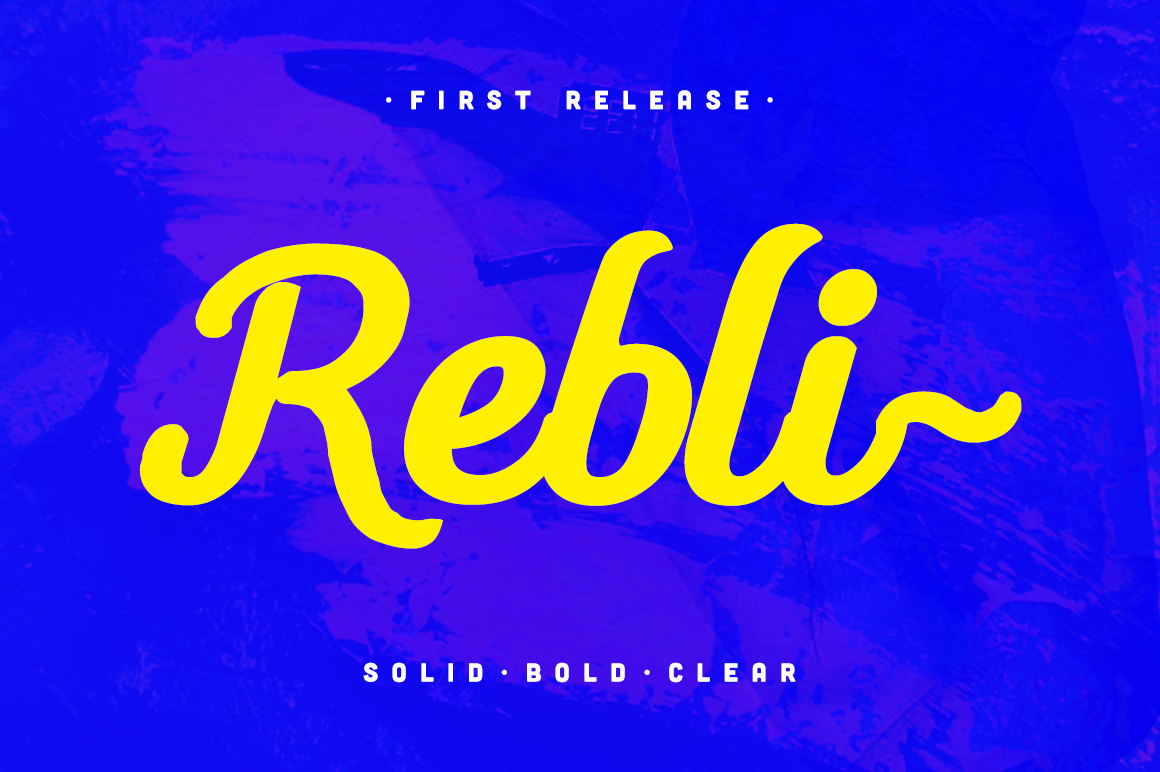
A fonte Rebli Script é perfeita para quem procura uma fonte que não apenas complementa sua identidade visual, mas também reforça seu estilo único. Este conjunto de fontes calligraficas vem com letras maiúsculas e minúsculas, bem como números, permitindo-lhe explorar diversas aplicações em seus projetos digitais. Seja para tornar mais expressivo a sua marca, incorporando elementos artesanais em suas peças de logotipo, dando vida à mensagens autorais ou mesmo personalizando sua presença nas mídias sociais e embalagens de produtos, esta fonte é uma escolha inteligente. A Rebli Script oferece um toque sofisticado e criativo para seus projetos digitais, ajudando você a destacar em seu mercado.